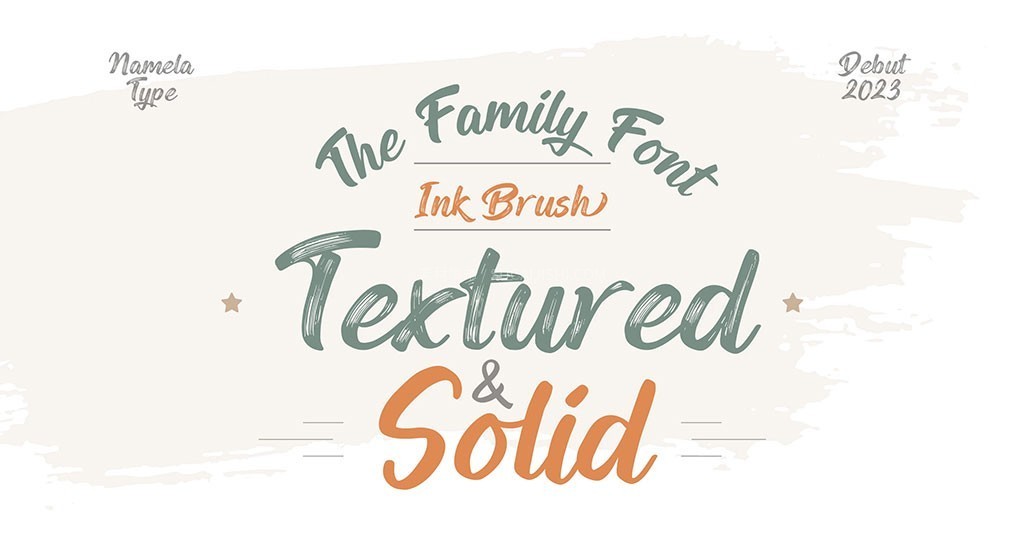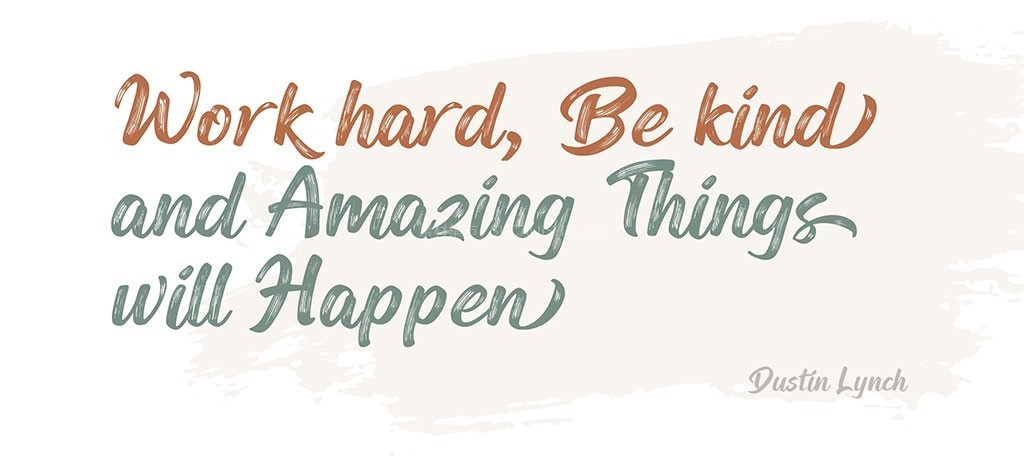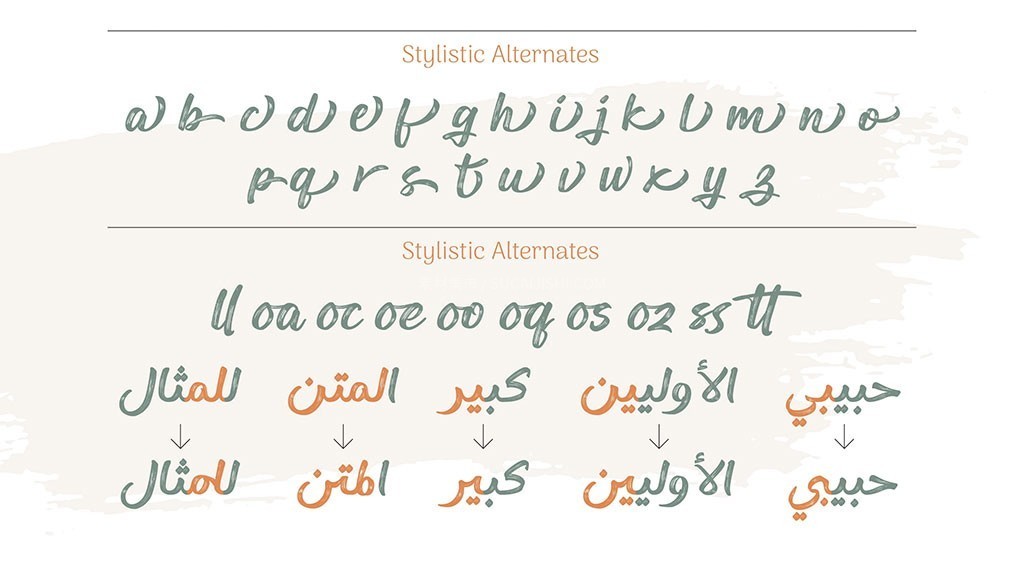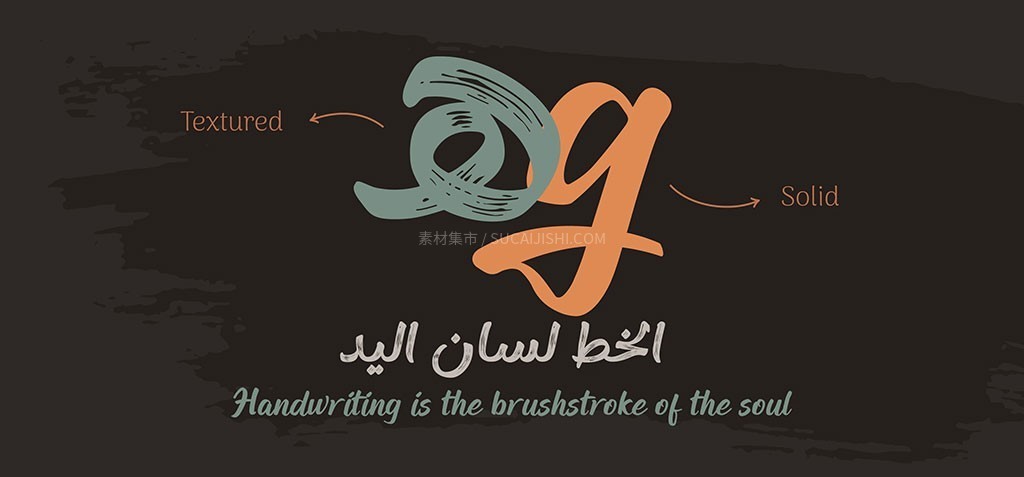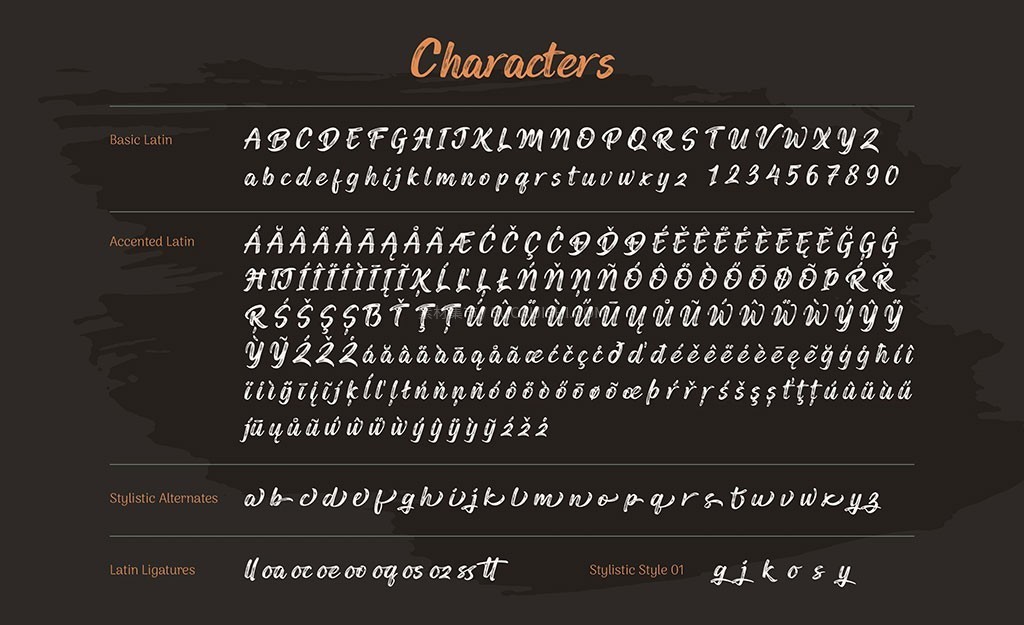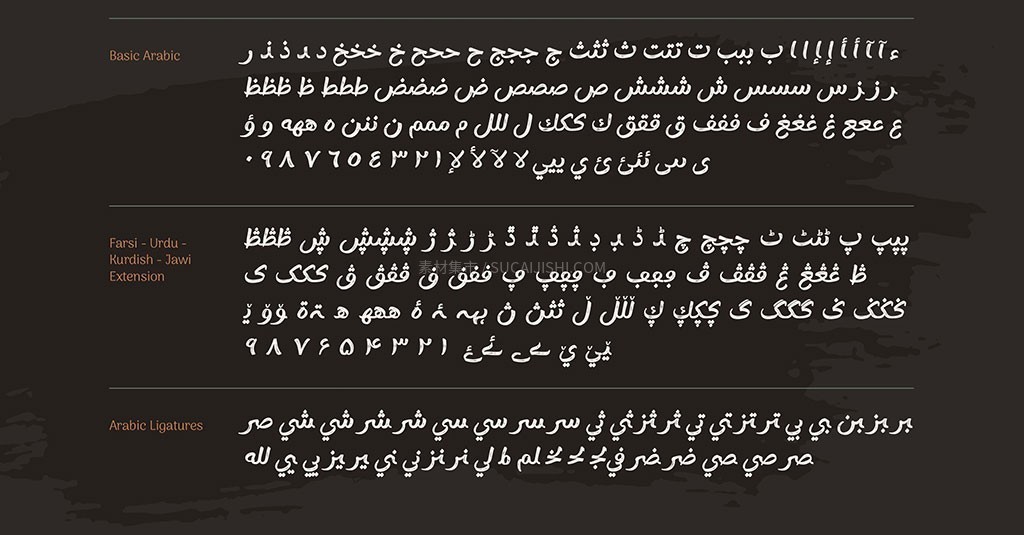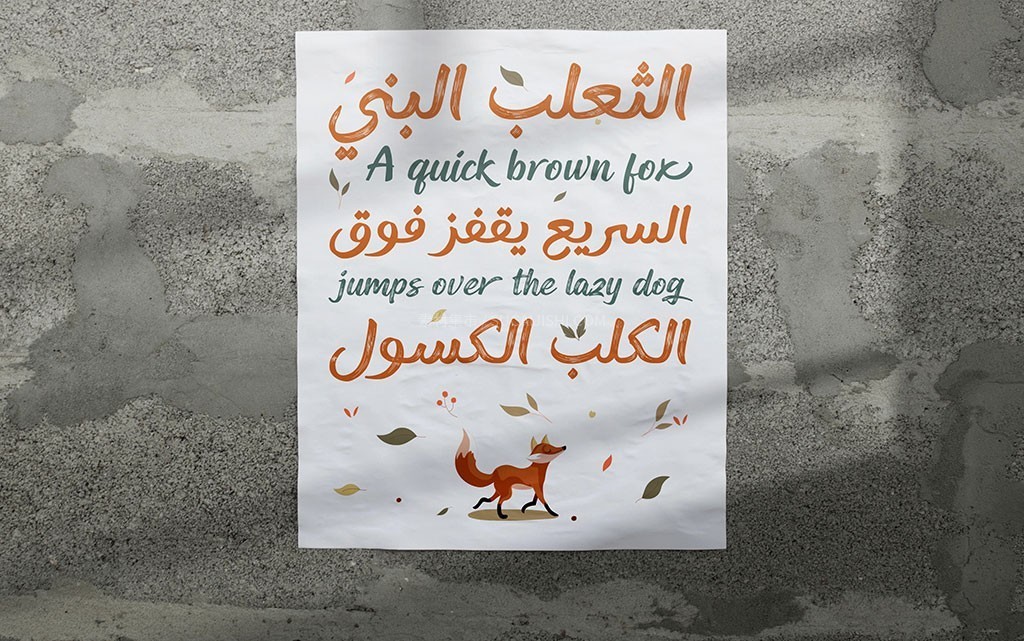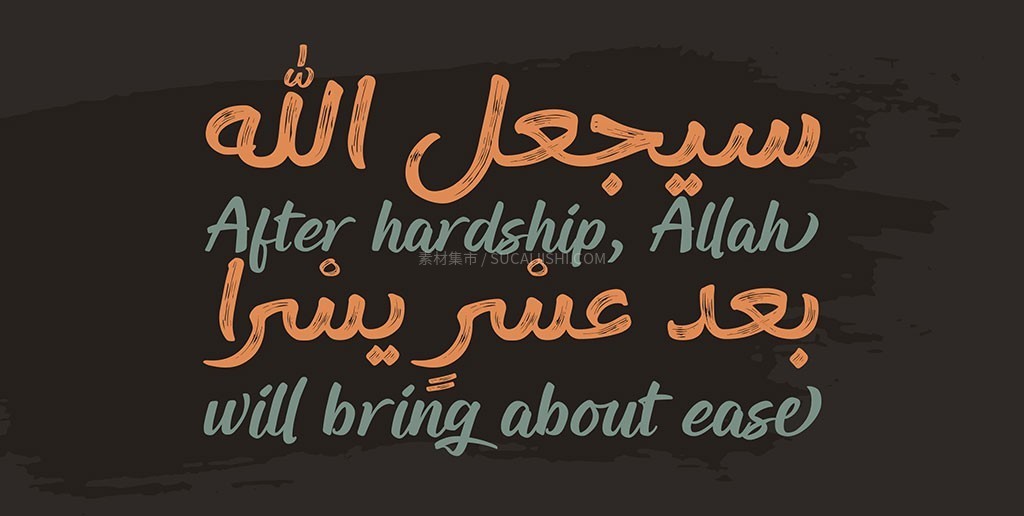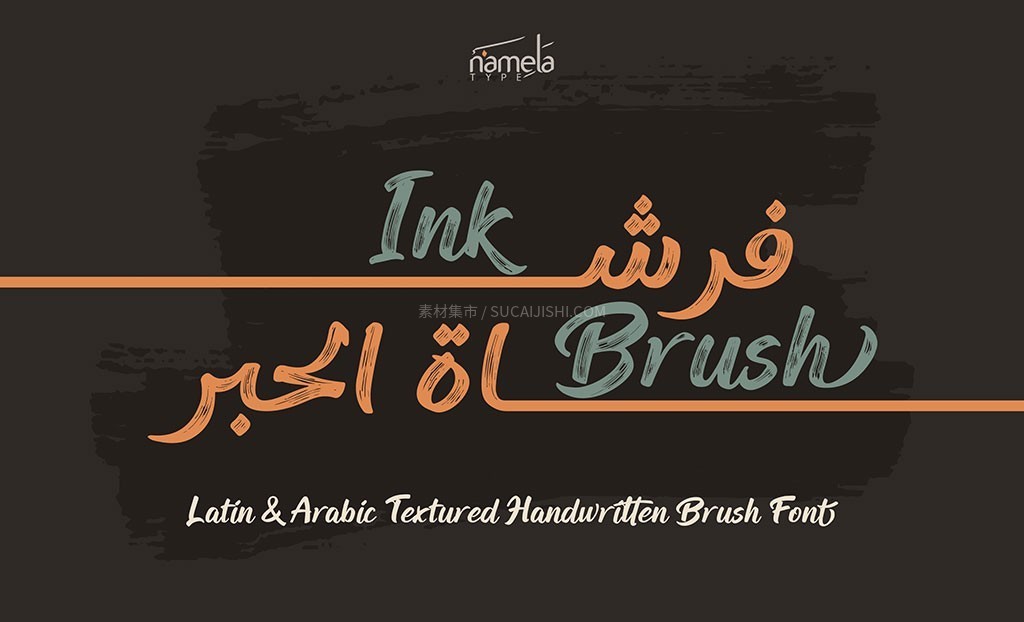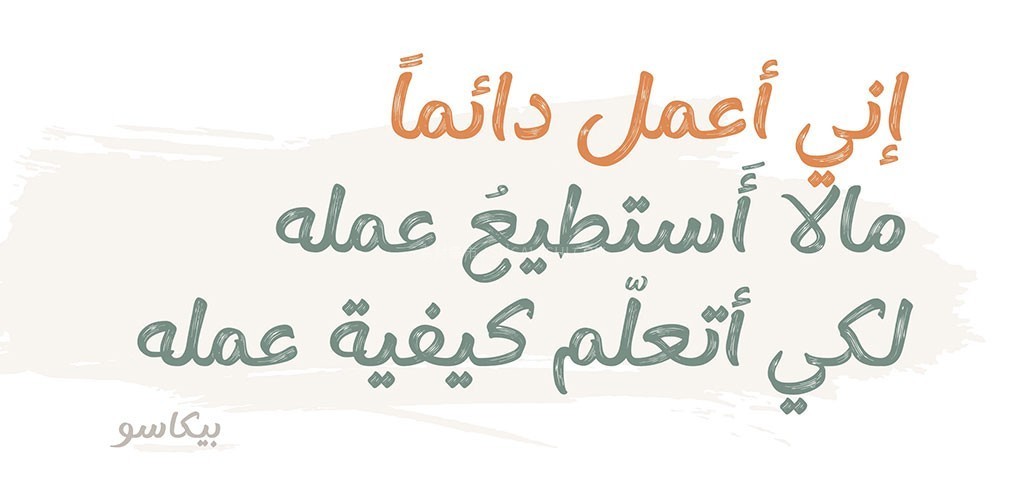
Ink Brush 复古手刷阿拉伯字体
这款复古风水墨笔刷字体真的绝了!它最大的特色就是自带那种超级真实的“干笔刷”纹理肌理,排版出来的字行云流水,视觉表现力直接拉满。最棒的是它不仅包含拉丁字母,还支持超优雅的阿拉伯字母(纳斯赫体),两套语言搭配在一起极度和谐高级!
套装里贴心准备了“纹理版”和“实心版”两个字族版本。想要那种随性手工艺术感的直接用纹理版,需要清晰精准视觉的就选实心版。无论你是想要质朴的手绘风,还是干净专业的视觉排版,这一套都能轻松拿捏,赶紧码住给你的创意作品注入灵魂吧!